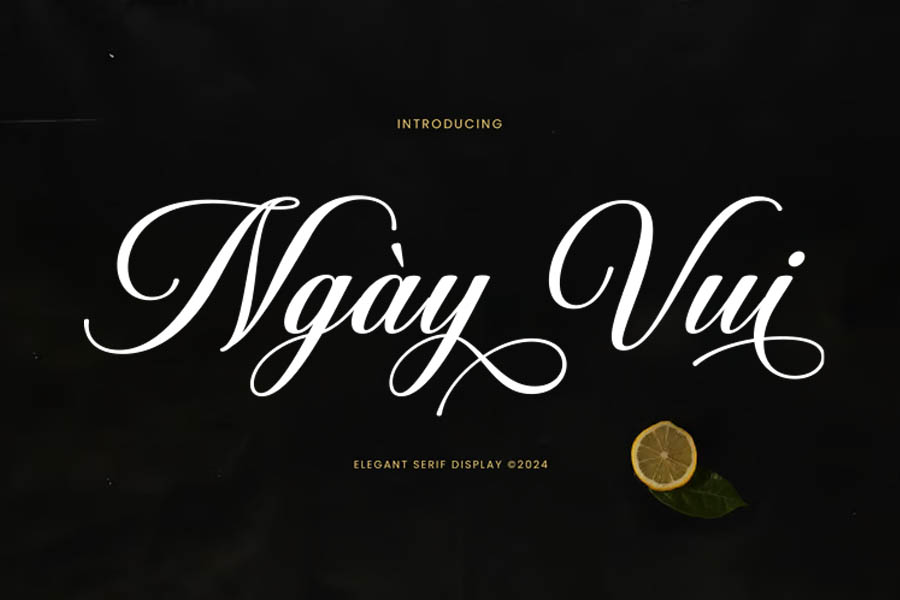
Tạo điểm nhấn thanh lịch cho thiết kế với font chữ mềm mại
Font chữ mềm mại là một phần không thể thiếu trong thiết kế đồ họa và website hiện đại. Những font chữ này không chỉ tạo cảm giác dễ chịu mà còn mang lại sự thanh lịch và chuyên nghiệp cho các sản phẩm thiết kế. Font chữ mềm thường được sử dụng trong các lĩnh vực như thời trang, làm đẹp, nội thất, và các dịch vụ cao cấp. Trong bài viết này, chúng ta sẽ cùng khám phá lý do vì sao font chữ mềm mại lại quan trọng và cách lựa chọn, sử dụng chúng sao cho hiệu quả.
Font chữ mềm mại có đặc điểm là các đường nét cong, uyển chuyển, giúp tạo ra cảm giác dễ chịu và thư giãn cho người đọc. Điều này đặc biệt quan trọng trong các thiết kế hướng đến người dùng cuối như website, ứng dụng di động hay tài liệu quảng cáo. Một font chữ mềm có thể làm cho nội dung trở nên thân thiện hơn, dễ đọc hơn, từ đó cải thiện trải nghiệm người dùng.
Font chữ mềm thường mang đến vẻ đẹp thanh lịch, sang trọng, phù hợp với các thiết kế cần sự tinh tế. Các thương hiệu cao cấp, các sản phẩm thời trang, và những ấn phẩm nghệ thuật thường ưu tiên sử dụng loại font này để tạo điểm nhấn và thể hiện phong cách riêng.
Sự phong phú của các font chữ mềm uyển chuyển, mềm mại giúp nhà thiết kế có nhiều lựa chọn hơn trong việc sáng tạo. Từ các font chữ có nét cổ điển như Serif cho đến các font hiện đại như Sans-Serif, mỗi loại đều có thể mang lại một phong cách khác nhau, đáp ứng được nhiều nhu cầu thiết kế đa dạng.
Dưới đây là danh sách top 08 font chữ mềm mại đang được ưa chuộng, mỗi kiểu chữ đều mang đến sự thanh thoát và dễ chịu khi sử dụng. Hãy cùng S99.vn xem qua để có lựa chọn cho thiết kế của riêng mình bạn nhé!
TH Maryatha là một phiên bản Việt hóa tuyệt vời của font chữ mềm mại, mang đậm nét cá nhân và sự tự nhiên của việc viết tay bằng bút chì màu. Với thiết kế chân thực và chi tiết, font chữ này không chỉ là một công cụ truyền tải thông điệp mà còn là một phương tiện nghệ thuật trong thiết kế Typo và Poster. TH Maryatha mang đến sự gần gũi và ấm áp như chính nét viết tay của bạn, nhưng lại được thực hiện với độ tinh tế và chất lượng cao. Điều này làm cho mỗi từ và câu trở nên sống động, phù hợp để sử dụng trong các bài thơ, trang trí, hay thậm chí các dự án sáng tạo nghệ thuật.
TH Maginia Việt hoá là font chữ mang đậm phong cách hiện đại và sáng tạo bằng cách kết hợp tinh tế giữa các đường cong mềm mại và các góc cạnh sắc sảo. Với mỗi nét vẽ chữ, nó tỏa ra sự tinh tế và hiện đại, hòa quyện giữa nét tròn mềm mại và đường thẳng thanh thoát. Bố cục của từng ký tự được thiết kế sao cho hài hòa và dễ đọc, với sự điều chỉnh tỉ mỉ từng chi tiết để tạo ra một font chữ độc đáo và thú vị. Các đường nét trong TH Maginia được xử lý mượt mà và chính xác, tạo cảm giác hiện đại và thích hợp với nhiều mục đích sử dụng, từ thiết kế đồ họa đến in ấn và web design.
TH Massillo là sự lựa chọn hoàn hảo cho việc thiết kế thiệp cưới và lễ cưới nhờ vào sự thanh lịch và tinh tế của nét viết tay mềm mại, uốn lượn. Với đường nét cong vòng nhẹ nhàng và sự cân đối trong từng nét chữ, font TH Massillo mang đến một cảm giác dịu dàng và sang trọng.
Đặc điểm đáng chú ý của font chữ này là sự mềm mại trong từng chi tiết, từ những đường thẳng mượt mà cho đến những vòng cung uyển chuyển. Sự duyên dáng và thướt tha của TH Massillo làm nổi bật văn bản, làm cho các từ và câu trở nên đẹp mắt và thu hút ngay từ cái nhìn đầu tiên.
Các nét chữ trong font TH Manchester thường được thiết kế tròn trịa, có độ nghiêng nhẹ, tạo cảm giác mượt mà và tự nhiên. Đặc điểm nổi bật của font chữ này là sự kết hợp hài hòa giữa sự cổ điển và hiện đại. Chữ viết tay trong font này có nét mềm mại, tươi mới và rất dễ đọc. Với việc Việt hóa, TH Manchester mang đến sự thân thiện, gần gũi nhưng không kém phần lịch lãm và sang trọng. Với sự hòa quyện giữa nét truyền thống và sự đương đại, font chữ TH Manchester Việt hóa là một lựa chọn lý tưởng cho những ai đang tìm kiếm một phong cách chữ viết tay đặc biệt và độc đáo.
Font chữ TH Maistoray mang đến một cảm giác mềm mại và thanh thoát như những nốt nhạc nhẹ nhàng trôi qua trên tầng không. Với đường nét cong vòng và sự phối hợp hài hòa giữa các yếu tố, font chữ này như một bản nhạc êm dịu với những nét vẽ tinh tế và sự tinh tế trong từng chi tiết. Các ký tự của TH Maistoray được thiết kế để tạo ra một cảm giác thân thiện và dễ chịu, phù hợp với các thiết kế có yêu cầu về sự nhẹ nhàng và tinh tế như thiệp cưới, logo, tiêu đề phim, tiêu đề sách... Với TH Maistoray, việc sáng tạo và thể hiện cá tính trong thiết kế văn bản trở nên dễ dàng hơn bao giờ hết.
Font chữ viết tay TH Migratory là một trong những kiểu chữ ký độc đáo và sôi động. Với đường nét mềm mại và phong cách tự do, nó mang đến một cảm giác năng động và cá tính. Các đường viết cong vòng và những nét chấm phá tạo nên sự tinh tế và sự khác biệt cho chữ ký này. H Migratory thường có kích thước vừa phải, không quá to mà không quá nhỏ, đủ để thu hút sự chú ý mà không gây quá tải cho mắt người đọc. Sự tự tin và sự linh hoạt của nét viết tạo nên một điểm nhấn đặc biệt trong bất kỳ văn bản nào nó xuất hiện. Đây không chỉ là một chữ ký mà còn là một biểu tượng của sự riêng biệt và phong cách.
Font chữ mềm mại đóng vai trò quan trọng trong việc tạo nên sự khác biệt và nâng cao tính thẩm mỹ cho các sản phẩm thiết kế. Bằng cách lựa chọn và sử dụng font chữ mềm một cách hợp lý, bạn có thể mang lại trải nghiệm tuyệt vời cho người dùng, tạo dựng hình ảnh thương hiệu thanh lịch và chuyên nghiệp. Hãy thử nghiệm và khám phá các loại font chữ mềm mại để tìm ra phong cách phù hợp nhất với nhu cầu thiết kế của bạn.